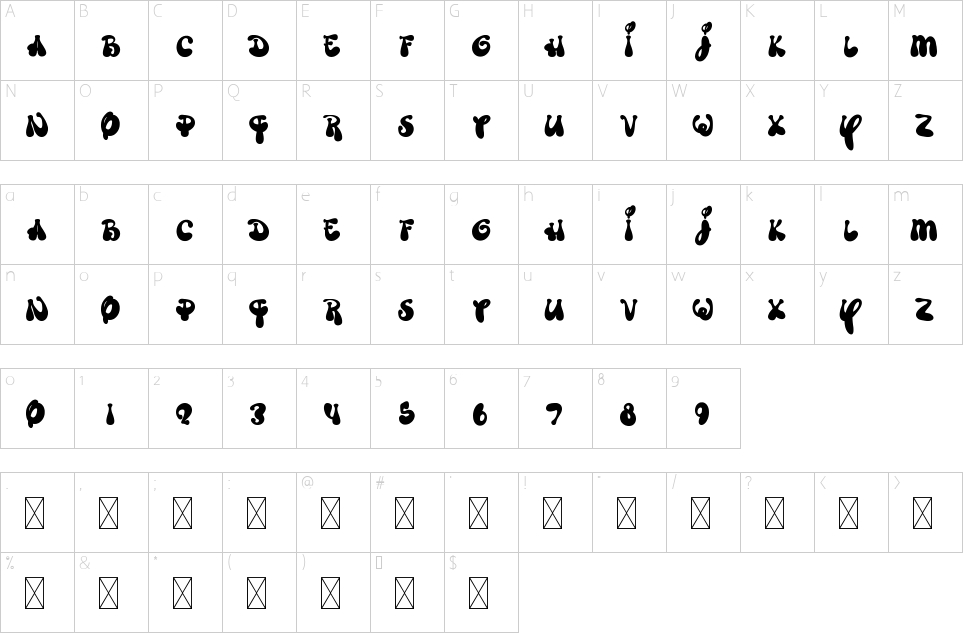
Aqui está uma descrição em português para a página de download da font ‘Disco Font’: Aproveite as cores vibrantes e os detalhes deslumbrantes da disco font, criada pelo designer FreshTypeINK. Esta font é perfeita para criar textos enérgicos e divertidos que se destacam em qualquer cenário. Não importa se você está trabalhando no Windows ou Mac, a Disco Font pode ser facilmente aplicada em seus projetos digitais. Com seu design cheio de vida e vibrante, ela tornará sua escrita única e impressionante. A font disco foi descarregada 98 vezes e não podemos deixar de comentar sobre o seu impacto no design digital atual. Se você está procurando por uma maneira para introduzir um toque especial em seus trabalhos, esta pode ser a solução perfeita. Desfrute do brilho vibrante da Disco Font.